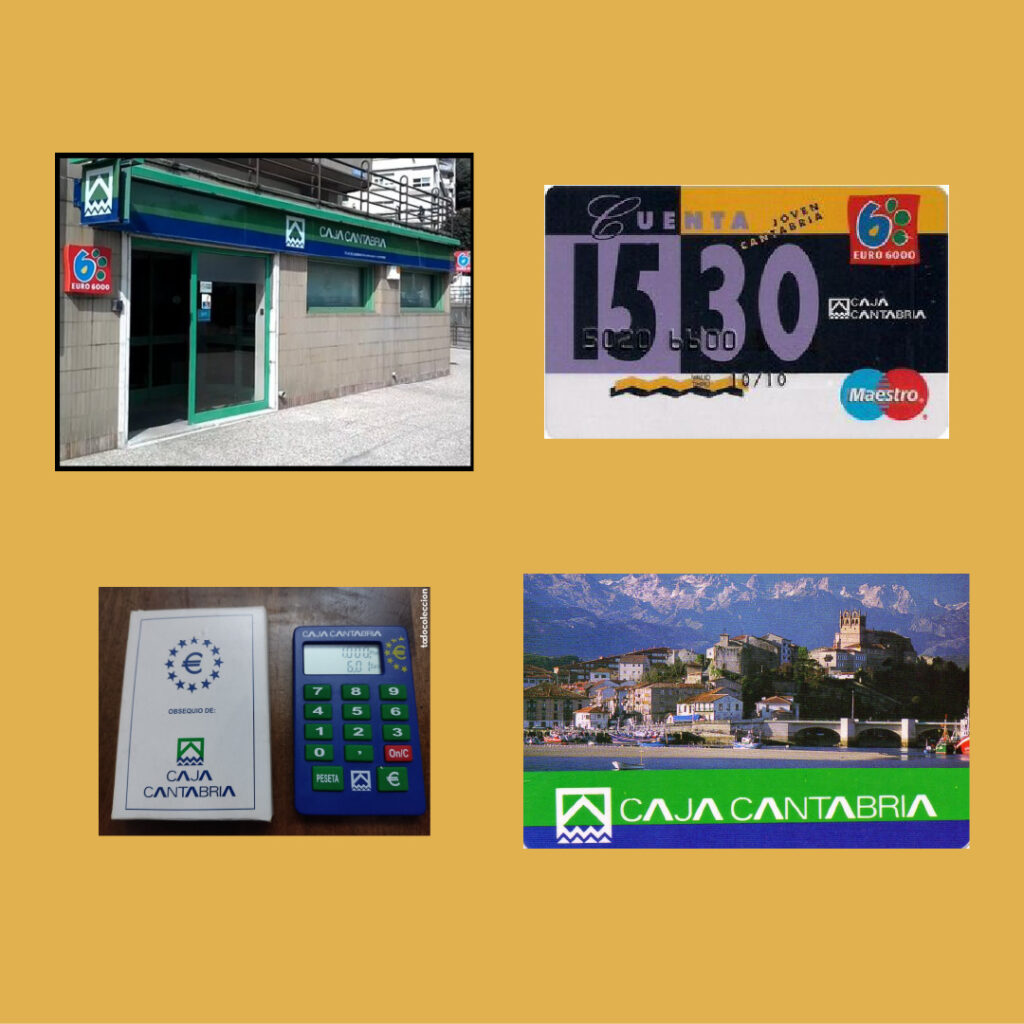
Caja Cantabria
Si hay una imagen que perdura en nuestra memoria colectiva es la de Caja Cantabria, con esa tipografía tan característica y su logo.
Caja Cantabria fue el  nombre comercial de la última época del banco, antes de ser comprado por Liberbank en 2011. Nacida en 1898 como «Monte de Piedad de Alfonso XIII y Caja de Ahorros de Santander», hasta la década de 1980 donde ya se denominaría Caja de Ahorros de Santander y Cantabria y finalmente Caja Cantabria. Tras la adquisición de Liberbank, desde 2014 podemos ver el isotipo vinculado a la propia Fundación Caja Cantabria, como entidad cultural.
Recordar que hubo un gran rótulo con el logo en el tejado de un edificio de la calle Jesús del Monasterio hasta 2015, que fue retirado por riesgo.